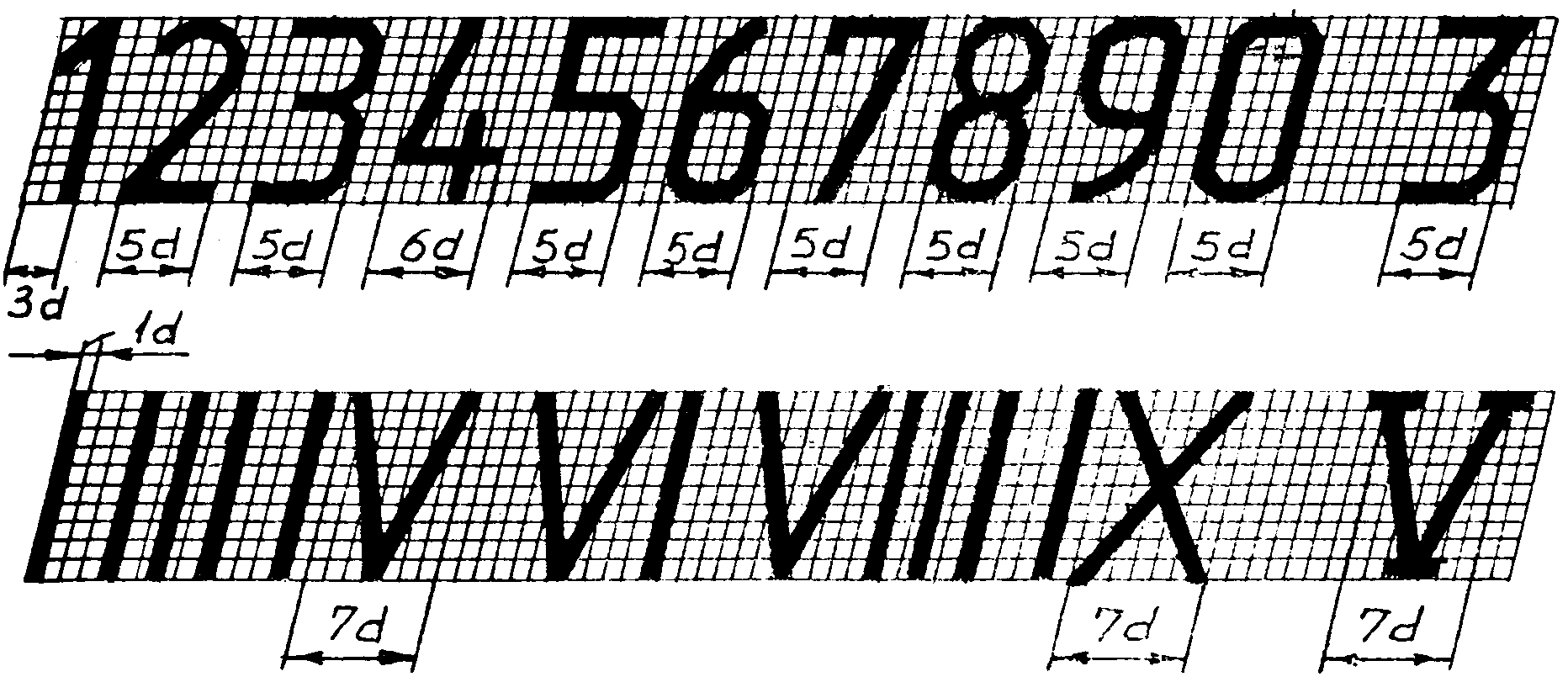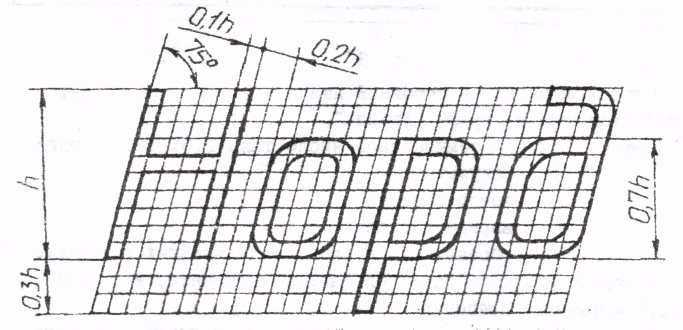
Как начертить букву а: Буквы для черчения. Чертежный шрифт. Алфавит. Правила написания прописных букв и цыфр
Буквы для черчения. Чертежный шрифт. Алфавит. Правила написания прописных букв и цыфр
Шрифт (от нем. Schrift) — это рисунок, начертание букв ка кого-либо алфавита, цифр и знаков.
Шрифты чертежные (ГОСТ 2.304-81) предназначены для выполнения надписей, начертания условных знаков и размерных чисел на чертежах. Для выполнения надписей в черчении используют ГОСТ. ГОСТ устанавливает номера чертежных шрифтов (1,8; 2,5; 3,5; 5; 7; 10; 14; 20; 28; 40) русского, латинского и других алфавитов.
Первый стандарт «Шрифты для надписей» был разработан и утвержден в 1919 г.
Номер шрифта соответствует высоте (h) прописной буквы. Например, шрифт № 5 имеет высоту прописной буквы, равную 5 мм.
Высота буквы измеряется перпендикулярно к основанию строки. Шрифт выполняется с наклоном в 75° (ГОСТом допускается выполнять надписи чертежным шрифтом без наклона).
Для удобства написания букв чертежного шрифта выстраивают вспомогательную сетку (рис.
Используя углы 45° и 30° угольников, строят наклон букв в строке, равный 75°.
Рассмотрите начертание букв чертежного шрифта (рис. 35— 37). Они различаются наличием горизонтальных, вертикальных, наклонных линий и закруглений, шириной и высотой. На рисунках показана (стрелками) последовательность начертания каждой буквы.
Рис. 35. Начертание прописных букв, состоящих из горизонтальных и вертикальных элементов, и построение вспомогательной сетки
рис. 36. Начертание прописных букв, состоящих из горизонтальных, вертикальных и наклонных элементов
Рис. 37. Начертание прописных букв, состоящих из прямолинейных и криволинейных элементов
Рис.
38. Начертание строчных букв, отличающихся от начертания прописных букв
Как вы, наверное, уже заметили, начертания многих строчных и прописных букв не отличаются между собой, например К — к, О — о и др. Начертание некоторых строчных букв отличается от начертания прописных (рис. 38).
При выполнении надписей следует учитывать, что нижние элементы прописных букв Д, Ц, Щ и верхний элемент буквы Й выполняют за счет расстояния между строк.
3. Размеры букв чертежного шрифта
Несмотря на то что расстояние между буквами определено стандартом, оно должно изменяться в зависимости от того, какое начертание имеют рядом стоящие буквы. Например, в слове РАБОТА (рис. 39, а) расстоянием между буквой P и A, T и А необходимо пренебречь (т. е. расстояние должно быть равно нулю), поскольку их начертание зрительно создает достаточный межбуквенный просвет. По этой же причине стандартное расстояние между буквами Б и О, 0 и T следует сократить вполовину.
Рис. 39. Учет межбуквенного просвета при написании слов: а — правильно; б — неправильно
Рис. 40. Цифры и знаки
Начертание цифр и знаков показано на рисунке 40. (При выполнении чертежей выбирайте высоту шрифта не менее 3,5 мм.)
Шрифт для надписей на чертеже (Чертежный шрифт) — Тема Линии чертежа — Уроки черчения — Каталог статей
Все надписи на чертежах должны быть выполнены чертежным шрифтом (рис. 24).
Начертание букв и цифр шрифта устанавливается стандартом. Стандарт определяет высоту и ширину букв и цифр, толщину их линий обводки, расстояние между буквами, словами и строками. Чтобы научиться надписывать чертежи стандартным шрифтом, надо знать не только характер начертания букв и цифр, но также и их размеры.
Стандарт устанавливает следующую высоту (она обозначается h, читается «аш») прописных (заглавных) букв и цифр: 2,5; 3,5; 5; 7; 10 и 14 мм. Высота прописных букв (рис. 25) в миллиметрах соответствует размеру шрифта.
Ширина большинства прописных букв равна 4/7 высоты.
Исключение составляют буквы Ж, Ф, Ш, Щ, Ы, Ю, ширина которых равна 6/7 h, и букв А и М, ширина которых равна 5/7 h, т. е. немного меньше высоты. Нижние и боковые отростки букв Д, Ц, Щ, Ъ, цифры 4 и верхний элемент буквы Й выполняются зa счет промежутков между строками и буквами
Эти соотношения установлены для основного чертежного шрифта.
Однако стандарт разрешает использовать и широкий шрифт. Ширина букв такого шрифта больше тех же букв основного шрифта на 1/7 h.
Буквы и цифры чертежного шрифта имеют наклон к линии строки примерно 75° (рис. 25). Некоторые надписи допускается выполнять без наклона.
Высота строчных букв равна 5/7 высоты прописных букв
(рис. 25), что примерно соответствует высоте следующего меньшего размера шрифта.
Например, высота строчных букв для шрифта 10 будет равна 7 мм. Исключение составляют буквы б, в, д, р, у и ф. Их общая высота равна Л.
Ширина строчных букв равна 3/7 h, кроме букв ж, т, ф, ш, щ, ы, ю, ширина которых равна примерно их высоте, и буквы м, имеющей ширину 4/7 h.
Цифры имеют те же размеры, что и прописные буквы,кроме цифры 1; ее ширина 2/7 h.Расстояние между буквами и цифрами в словах принимают равным 2/7 h, между словами и числами не менее ширины букв текста. Расстояние между нижними линейками строк должны быть равны не менее 1.5 h.